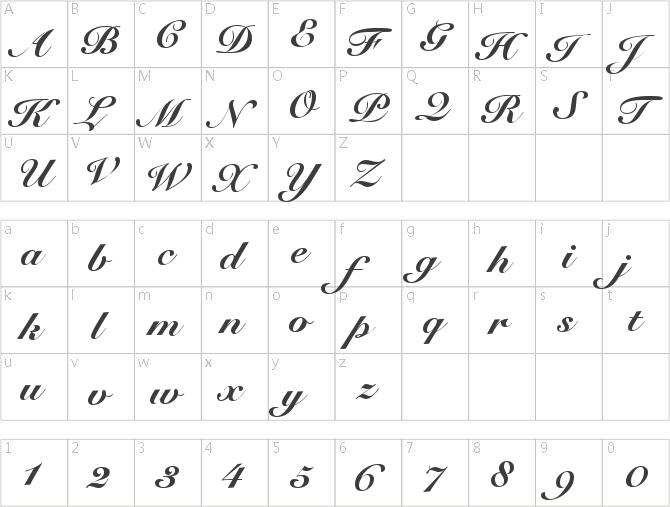
RoundhandBlack 詳情頁
字體名稱: Roundha
RoundhandBlack
RoundhandBlack字體字庫是一款讓人賞心悅目、百看不厭的英文字體,適合各類廣告和產(chǎn)品包裝設(shè)計應(yīng)用,字體大小0.07MB,格式為ttf字體,上傳用戶是凡客,作者/版權(quán)方為未知